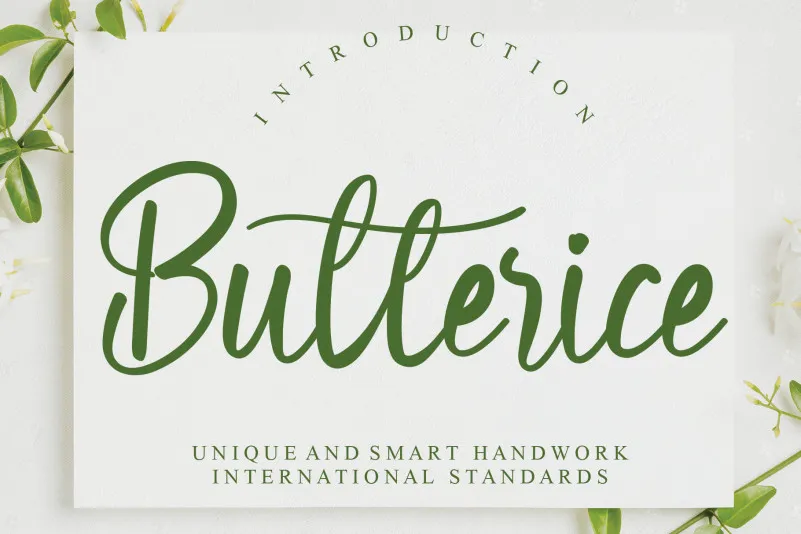
Butterice Script Font – Download Grátis
Descubra uma nova aventura com ‘Butterice Script Font’, criada pelo designer creativeletter. Esta fonte é uma explosão de detalhes criativos que vai revolucionar a forma como você apresenta texto em projetos digitais. Com linhas fluidas e arredondadas, essa fonte é perfeita para criar um estilo único e moderno em sua composição de design gráfico. Ela é ideal para nomes de marca, logotipos e qualquer projeto que exige uma sensação de sofisticação e criatividade. Onde há uma necessidade de expressar a personalidade através da escrita em projetos digitais, ‘Butterice Script Font’ se destaca. Suas formas delicadas e fluidas são perfeitas para criar um texto chamativo que destacará sua marca ou design no mercado digital. Estamos certos de que ‘Butterice Script Font’ não apenas agradará aos designers visuais, mas também ao público final que encontra beleza em detalhes meticulosamente criados. Descubra agora e transforme o estilo visual do seu projeto em algo inovador e único.